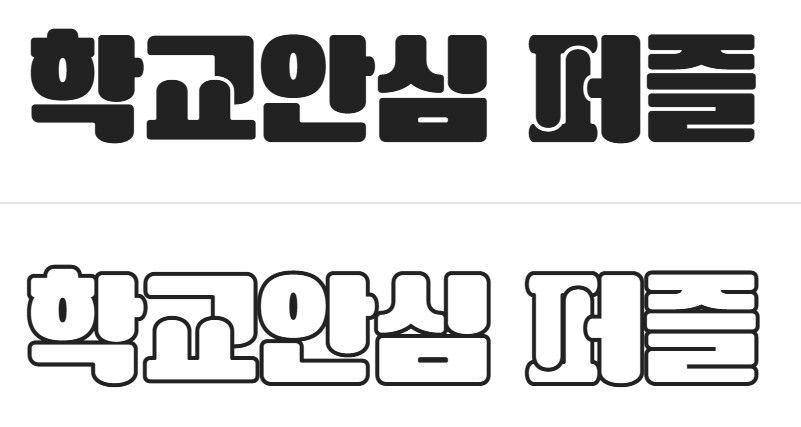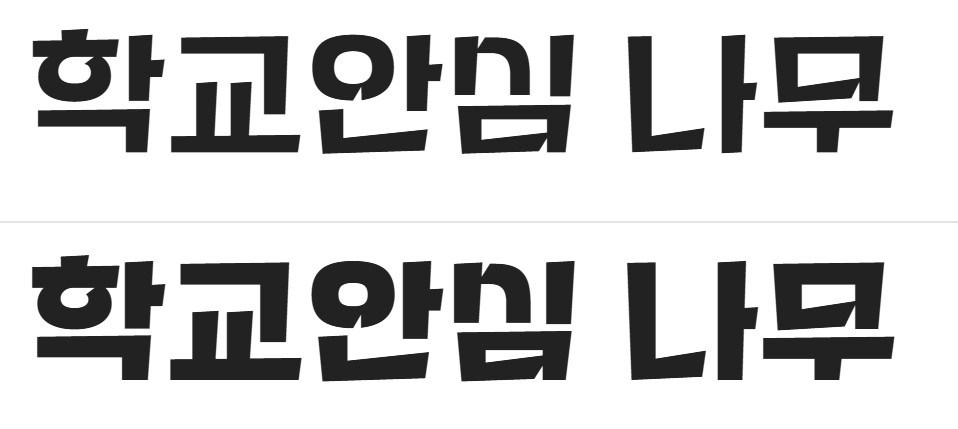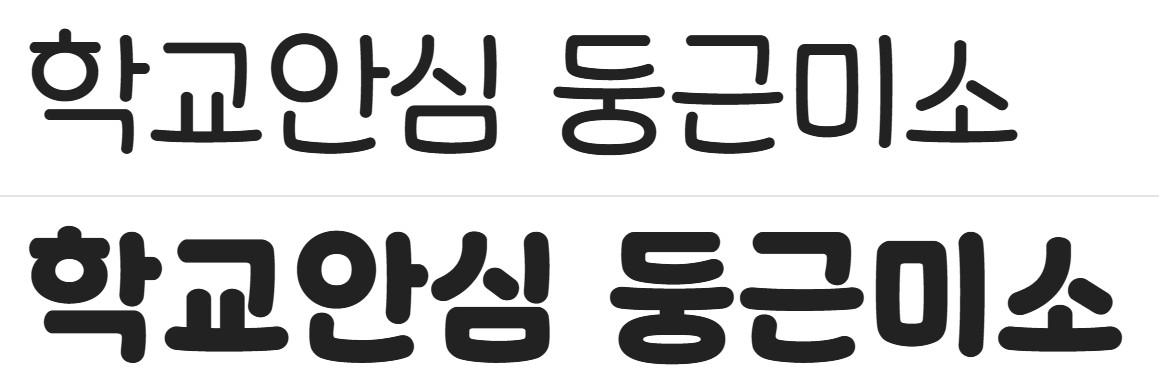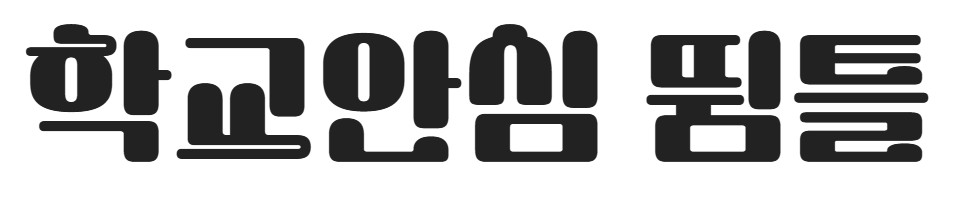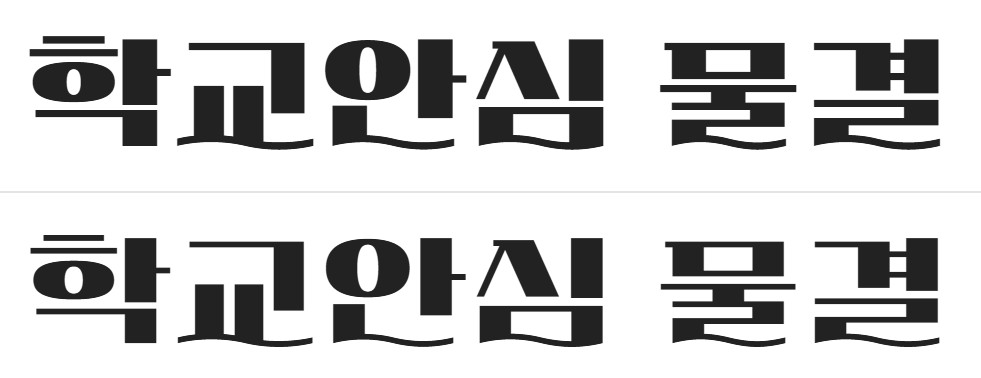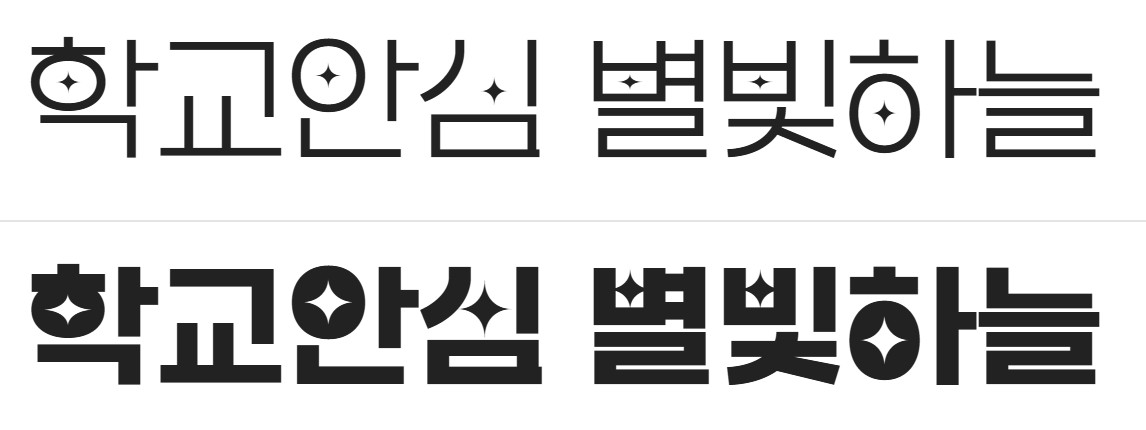
교육자료, 학급 소식지, 발표자료나 포스터를 만들 때 가장 먼저 눈에 띄는 건 바로 제목 폰트입니다. 제목은 콘텐츠의 첫인상을 좌우하니, 개성 있고 또렷한 서체를 고르는 것이 중요하죠. 오늘은 학교안심폰트 중 제목용으로 딱 좋은 서체 10종을 소개해드립니다.
학교안심폰트란 무엇인가요?
‘학교안심폰트’는 교육부와 한국교육학술정보원(KERIS)이 전국 초·중·고등학교 및 교육기관을 위해 제작한 무료 글꼴입니다. 이 폰트는 누구나 자유롭게 사용할 수 있도록 제공되며, 특히 상업적 이용까지 가능해 다양한 콘텐츠 제작에 매우 유용합니다.
이 폰트는 글꼴 저작권 문제로부터 교사와 학생, 교육기관을 보호하고, 안전한 교육 콘텐츠 환경을 조성하기 위한 목적에서 개발되었습니다. ‘학교안심폰트’라는 이름처럼 라이선스 걱정 없이 안심하고 사용할 수 있다는 점이 가장 큰 장점입니다.
제목용 폰트 10종 추천
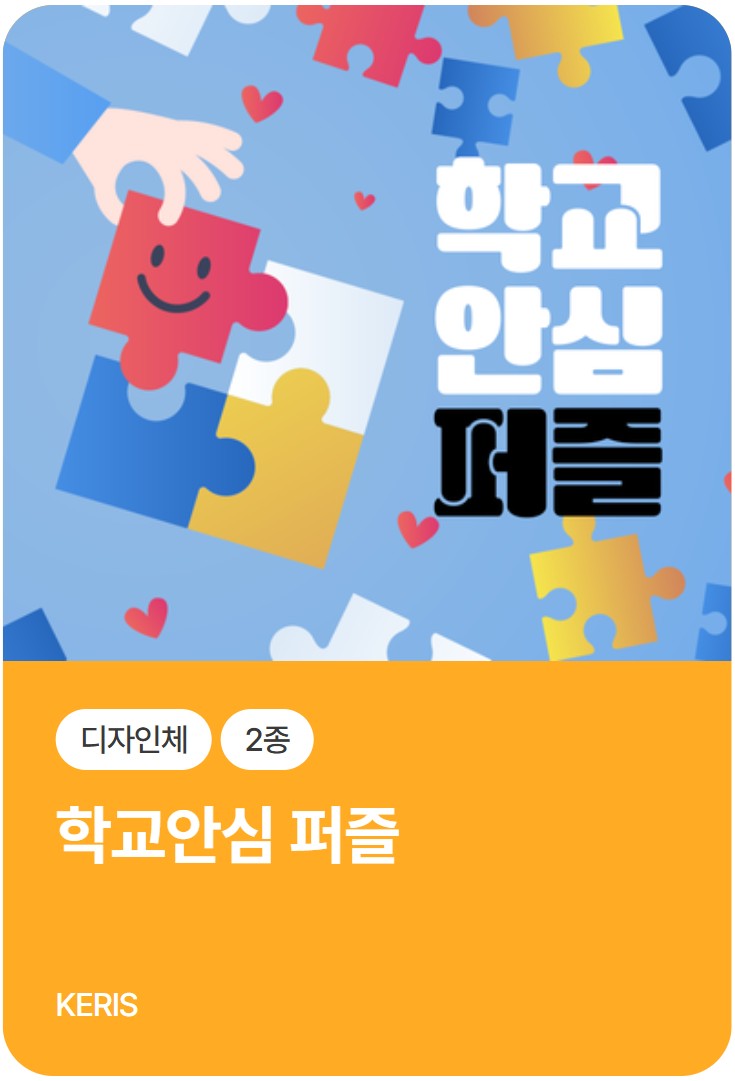
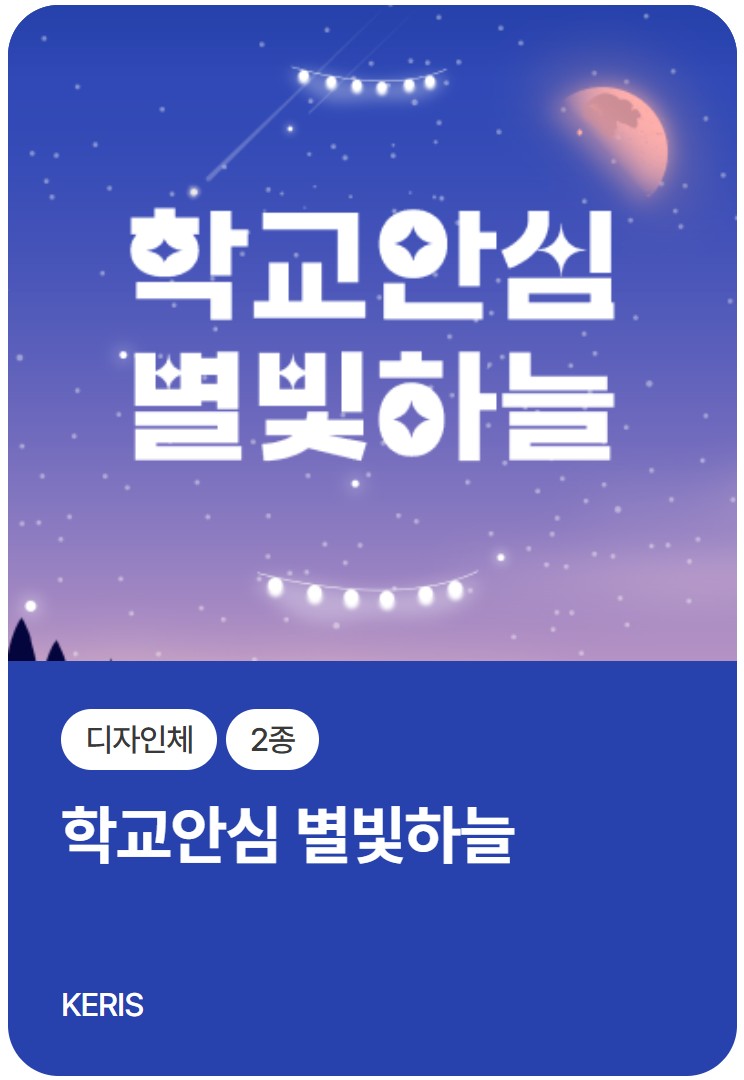
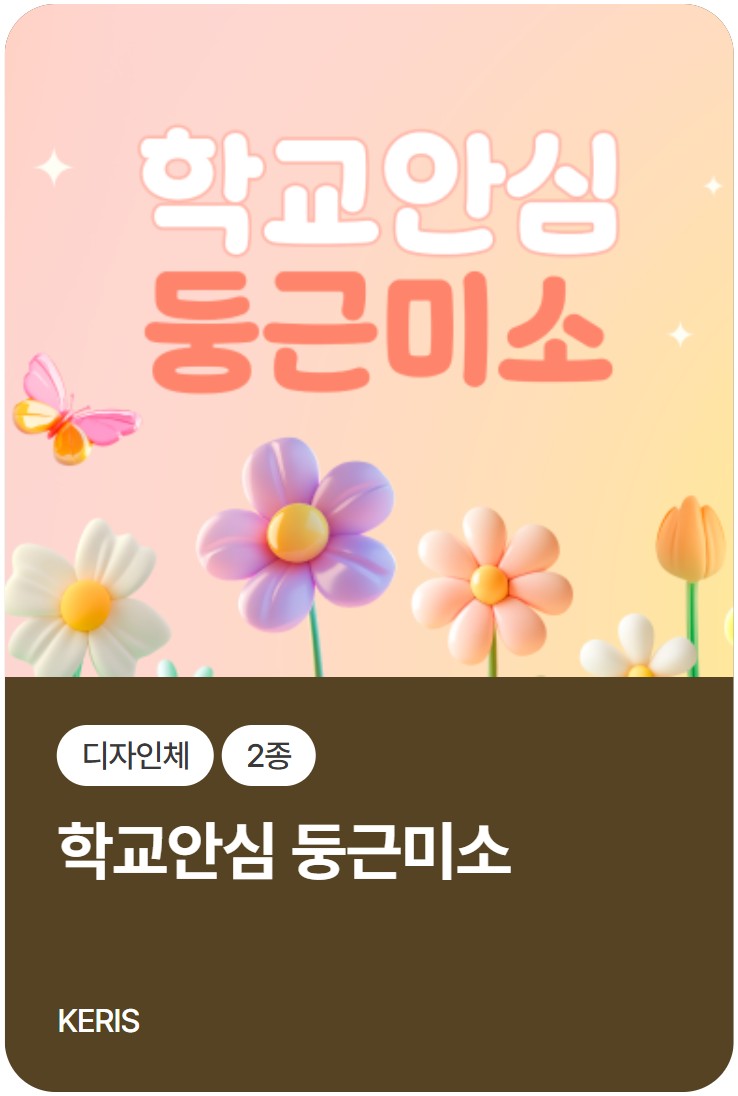
1. 학교안심 퍼즐
- 특징: 퍼즐 조각처럼 맞물린 독특한 구조
- 분위기: 창의적이고 유쾌한 느낌
- 용도: 퀴즈, 수학 놀이, 창의학습 자료 등에 적합
2. 학교안심 꽈배기
- 특징: 꽈배기처럼 꼬인 독특한 획이 돋보이는 개성 있는 서체
- 분위기: 장난스럽고 유쾌한 느낌
- 용도: 축제 포스터, 놀이 활동 제목 등에 적합
3. 학교안심 나무
- 특징: 자연스러운 굵기와 형태로 나무의 특징을 연상시키는 서체
- 분위기: 안정감 있고 친환경적인 분위기
- 용도: 환경 교육, 학급 규칙 포스터, 자연체험 안내문 등
4. 학교안심 둥근미소
- 특징: 둥글고 따뜻한 곡선으로 미소처럼 편안한 느낌
- 분위기: 친근하고 긍정적인 분위기
- 용도: 인사말 제목, 소개 자료, 학부모 안내문 등에 적합
5. 학교안심 뜀틀
- 특징: 높낮이와 리듬감이 느껴지는 활동적인 디자인
- 분위기: 활발하고 에너지 넘치는 느낌
- 용도: 체육대회, 놀이활동 안내 포스터 등
6. 학교안심 물결
- 특징: 물결치는 듯한 고딕과 곡선의 조화가 특징인 감성 서체
- 분위기: 부드럽고 정돈된 분위기
- 용도: 문학 행사, 학급 시화전, 안내판 등에 적합
7. 학교안심 별빛하늘
- 특징: 별빛을 형상화한 신비로운 분위기의 서체
- 분위기: 로맨틱하고 상상력 자극
- 용도: 과학의 날, 밤하늘 관련 콘텐츠, 창작 행사 제목
8. 학교안심 사물함
- 특징: 넓은 폭과 강한 대비, 일부 획의 기하학적 꺾임이 있어 시각적 포인트
- 분위기: 약간의 위트가 더해져 딱딱하지 않고 친숙함
- 용도: 교칙 안내문, 분실물 표지, 사물함 라벨, 교내 캠페인 포스터 등 정보를 전달할 때 적합
9. 학교안심 콧수염
- 특징: 위트 있는 곡선과 장식이 돋보이는 유머러스한 서체
- 분위기: 익살스럽고 독특한 인상
- 용도: 퀴즈 포스터, 유머 코너 제목, 교내 행사 홍보 등
10. 학교안심 봄방학
- 특징: 봄방학의 설렘을 담은 자유롭고 가벼운 손글씨 느낌
- 분위기: 산뜻하고 따스한 분위기
- 용도: 계절 소식지, 새 학기 알림장, 봄맞이 행사 포스터
제목 하나에도 폰트를 다르게 쓰면 분위기가 완전히 바뀝니다. 학교안심 정서적으로 안정되면서도 창의적인 분위기를 연출할 수 있어요. 여러분의 자료와 콘텐츠가 더 풍성해지길 바랍니다! 누구나 상업적으로 사용 가능합니다.😊